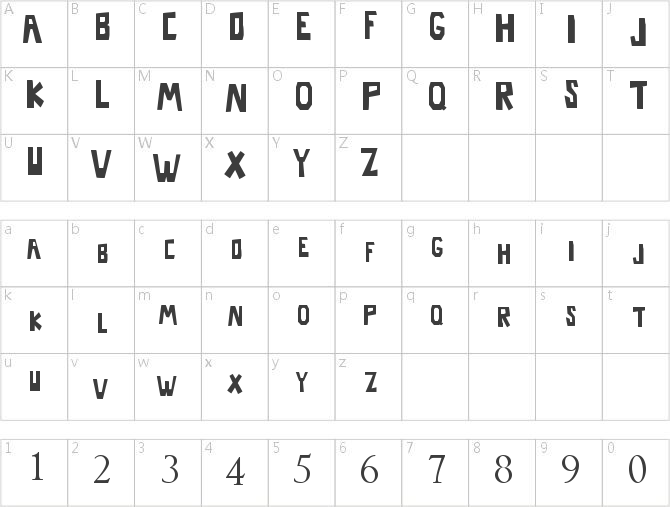
字體名稱(chēng): rocko
rocko
rocko介紹
rocko字體字庫(kù)是一款讓人賞心悅目、百看不厭的英文字體,適合各類(lèi)廣告和產(chǎn)品包裝設(shè)計(jì)應(yīng)用,字體大小0.02MB,格式為ttf字體,上傳用戶(hù)是……西央,作者/版權(quán)方為未知